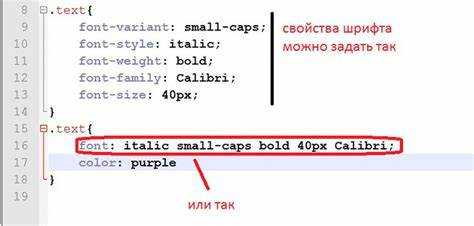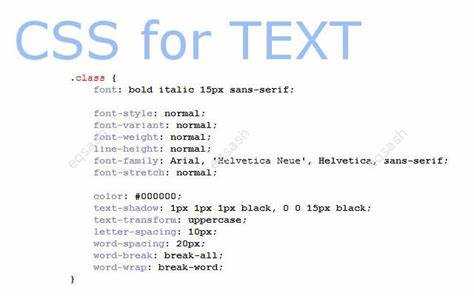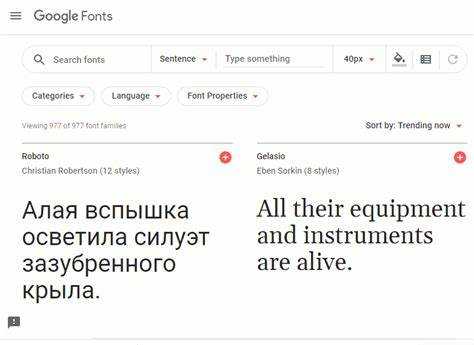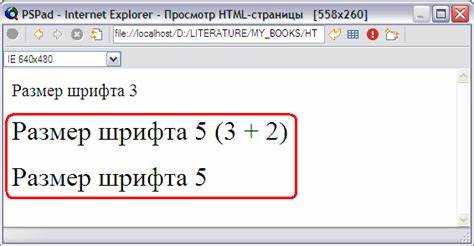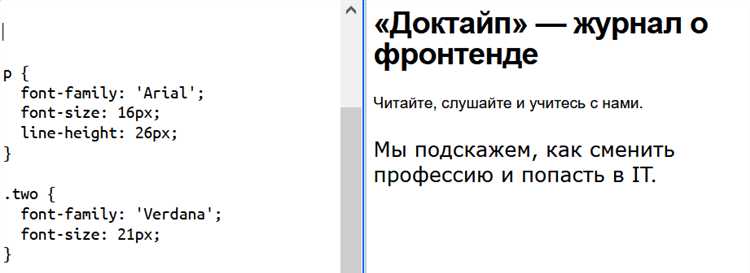
Выбор шрифта напрямую влияет на читаемость, восприятие и визуальную иерархию контента. В CSS для управления шрифтами используется свойство font-family, которое позволяет указать конкретный шрифт или список шрифтов с запасными вариантами. Например: font-family: «Roboto», Arial, sans-serif;.
Чтобы текст отображался корректно на всех устройствах, важно указывать не только желаемый шрифт, но и одну или несколько системных альтернатив. Это предотвращает проблемы с загрузкой нестандартных шрифтов и улучшает производительность. Последний элемент в списке – обычно родовое семейство: serif, sans-serif, monospace.
Для подключения нестандартных шрифтов используют правило @font-face или сторонние сервисы вроде Google Fonts. В случае с @font-face необходимо указать путь к файлу и задать уникальное имя: font-family: «MyCustomFont»; в сочетании с src: url(«myfont.woff2») format(«woff2»);.
Как задать семейство шрифтов с помощью свойства font-family
Свойство font-family
позволяет указать одно или несколько семейств шрифтов, которые браузер будет использовать для отображения текста. Указывается список через запятую: от предпочтительного к запасным.
Пример:
p {
font-family: "Segoe UI", Roboto, "Helvetica Neue", sans-serif;
}
Если первое семейство недоступно, браузер переходит к следующему. Последним всегда следует указывать универсальное семейство: serif
, sans-serif
, monospace
, cursive
или fantasy
.
Названия шрифтов с пробелами обязательно заключать в кавычки. Имена без пробелов можно указывать без кавычек.
Чтобы обеспечить кроссбраузерную совместимость, используйте минимум три семейства: основное, резервное и универсальное.
Некорректно:
body {
font-family: Arial Helvetica sans-serif;
}
Правильно:
body {
font-family: Arial, Helvetica, sans-serif;
}
Важно учитывать регистр символов в названиях шрифтов и использовать точное написание, особенно при подключении веб-шрифтов через @font-face
.
Подключив пользовательский шрифт, первым указывайте его название, затем резервные:
h1 {
font-family: "Open Sans", Verdana, sans-serif;
}
Избегайте указания только одного шрифта – это снижает адаптивность интерфейса при отсутствии шрифта у пользователя.
Чем отличаются шрифты с засечками и без, и как это указать в CSS
Шрифты с засечками (serif) имеют декоративные элементы на концах штрихов. Эти мелкие черточки улучшают читаемость длинного текста на бумаге и при умеренном размере на экране. Классические примеры – Times New Roman, Georgia.
Шрифты без засечек (sans-serif) лишены этих элементов. Они создают более строгий и современный визуальный эффект, особенно подходят для цифровых интерфейсов и заголовков. Примеры – Arial, Helvetica, Roboto.
В CSS семейство шрифта задаётся через свойство font-family. Чтобы указать тип, используйте ключевое имя семейства:
С засечками:
font-family: 'Georgia', serif;
Без засечек:
font-family: 'Arial', sans-serif;
Первым указывается предпочтительный шрифт, далее – резервное семейство. Это обеспечивает корректное отображение, если основной шрифт недоступен.
Не используйте системные названия без уточнения типа семейства. Например, font-family: serif;
применит шрифт по умолчанию, который может отличаться в разных браузерах и ОС.
Для строгого контроля внешнего вида – подключайте веб-шрифты через @font-face
или сервисы вроде Google Fonts, но всегда указывайте fallback-семейство для надежности:
font-family: 'Merriweather', serif;
Как подключить пользовательский шрифт через @font-face
@font-face позволяет использовать шрифты, которые не установлены у пользователя на устройстве. Это особенно важно для дизайнерской целостности и брендированных решений.
- Скачайте файл шрифта в формате .woff или .woff2. Эти форматы оптимальны по соотношению качества и размера.
- Сохраните файл в директории проекта, например,
/fonts/
. - Добавьте правило
@font-face
в ваш CSS:
@font-face {
font-family: 'MyFont';
src: url('/fonts/myfont.woff2') format('woff2'),
url('/fonts/myfont.woff') format('woff');
font-weight: normal;
font-style: normal;
font-display: swap;
}
font-family
– произвольное имя, по которому будет вызываться шрифт в стилях.src
– пути к файлам шрифта с указанием формата. Рекомендуется указывать несколько форматов для кроссбраузерной поддержки.font-display: swap
– позволяет отображать текст системным шрифтом до загрузки пользовательского, повышая скорость отрисовки.
Чтобы применить подключённый шрифт, используйте его имя в свойствах font-family
:
body {
font-family: 'MyFont', sans-serif;
}
Для кириллической поддержки убедитесь, что шрифт содержит необходимые глифы. Если нет, ищите версию с поддержкой расширенной кодировки (например, «Cyrillic Extended»).
Как использовать шрифты из Google Fonts в CSS
Для подключения шрифтов из Google Fonts необходимо выполнить два шага: импортировать нужный шрифт и применить его через CSS-свойство font-family
.
- Перейдите на сайт fonts.google.com.
- Выберите нужный шрифт, например, Roboto.
- Кликните по кнопке «Select this style» рядом с нужным начертанием (например, 400 или 700).
- В блоке «Use on the web» скопируйте тег
<link>
, начинающийся с<link href="https://fonts.googleapis.com/...
. - Вставьте этот тег в
<head>
вашего HTML-документа.
Пример подключения шрифта Roboto:
<link href="https://fonts.googleapis.com/css2?family=Roboto:wght@400;700&display=swap" rel="stylesheet">
После подключения, примените шрифт в CSS:
body {
font-family: 'Roboto', sans-serif;
}
Рекомендации по использованию:
- Указывайте резервные семейства:
sans-serif
,serif
,monospace
. - Не подключайте больше 2–3 гарнитур одновременно – это замедляет загрузку страницы.
- Используйте параметр
display=swap
для улучшения производительности и уменьшения FOUT (Flash of Unstyled Text). - При необходимости подключайте только нужные начертания и языковые подмножества, указывая их явно в URL.
Как задать размер шрифта с помощью свойства font-size
font-size определяет высоту символов текста. Единицы измерения бывают абсолютные (px, pt, cm) и относительные (em, rem, %, vw).
Для фиксированного размера чаще используют px: font-size: 16px;. Такой подход обеспечивает точный результат, но плохо масштабируется при изменении настроек браузера.
Относительные единицы масштабируются автоматически. em зависит от родительского элемента: font-size: 1.5em; увеличит размер на 150% от базового. rem ссылается на корневой элемент (html): font-size: 1.2rem; будет 1.2 × базовый размер.
Для адаптивного дизайна используют vw (проценты от ширины окна): font-size: 3vw;. Размер текста изменяется вместе с размерами экрана, но требует тестирования на разных устройствах.
Рекомендуется устанавливать базовый размер через html { font-size: 16px; }, а далее использовать rem – это упрощает масштабирование и делает дизайн предсказуемым.
Избегайте чрезмерного вложения em, чтобы избежать неожиданных значений. Используйте clamp() для гибкого размера: font-size: clamp(14px, 2vw, 18px); – текст масштабируется, но не выходит за указанные пределы.
Как задать начертание и насыщенность шрифта в CSS
Для изменения начертания и насыщенности шрифта в CSS используются свойства font-weight
и font-style
.
Свойство font-weight
позволяет изменять толщину шрифта. Оно может принимать значения от 100 до 900, где 400 соответствует нормальному весу шрифта, а 700 – жирному. Также доступные ключевые значения: normal
для обычной насыщенности и bold
для жирного текста. Например, чтобы задать шрифт с весом 600, используйте:
p { font-weight: 600; }
Свойство font-style
управляет наклоном шрифта. Оно может быть установлено в одно из значений: normal
(обычное начертание), italic
(курсив) или oblique
(наклонный). Курсив чаще всего используется для выделения фрагментов текста, например:
p { font-style: italic; }
Важно помнить, что не все шрифты поддерживают изменения насыщенности и наклона. Если заданный шрифт не имеет необходимого начертания, браузер может использовать альтернативные варианты шрифта, что может привести к нежелательному эффекту. Поэтому для максимального контроля над внешним видом текста следует выбирать шрифты, поддерживающие разнообразие начертаний, или использовать web-шрифты, такие как Google Fonts.
Когда требуется более тонкая настройка начертания, можно комбинировать font-weight
и font-style
, чтобы добиться нужного визуального эффекта. Например, для жирного курсива:
p { font-weight: bold; font-style: italic; }